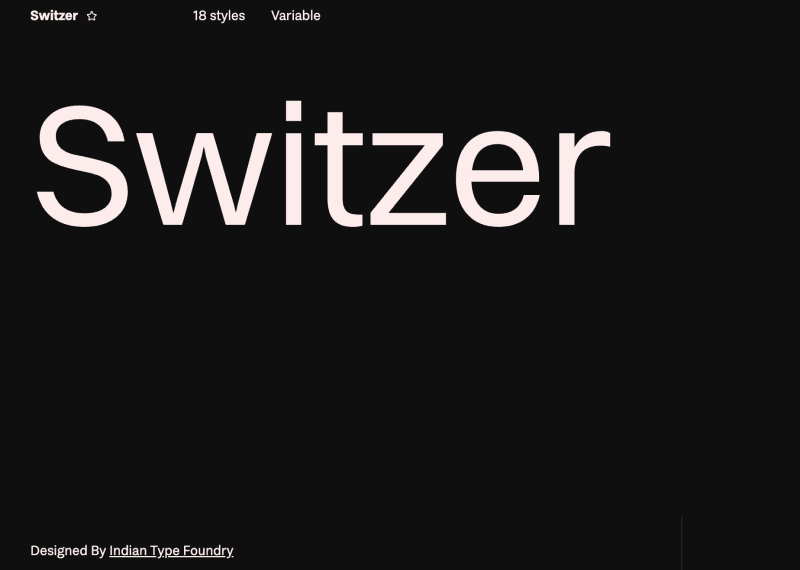
Switzer: Free Neo-grotesk Font in 18 Styles
Switzer ist eine neo-groteske serifenlose Schriftart, die von der Indian Type Foundry entworfen und veröffentlicht wurde. Diese kostenlose Schriftart ist insgesamt in 18 Stilen erhältlich, von dünn bis schwarz, und enthält auch eine Variable-Version. Mit ihren sauberen und regelmäßigen Formen ist diese Schriftart äußerst vielseitig und kann für Bücher, Logos, Magazine, Poster, Bildschirme, Websites und vieles mehr verwendet werden. Die Schriftart wird unter der Closed Source / ITF Free Font License veröffentlicht.